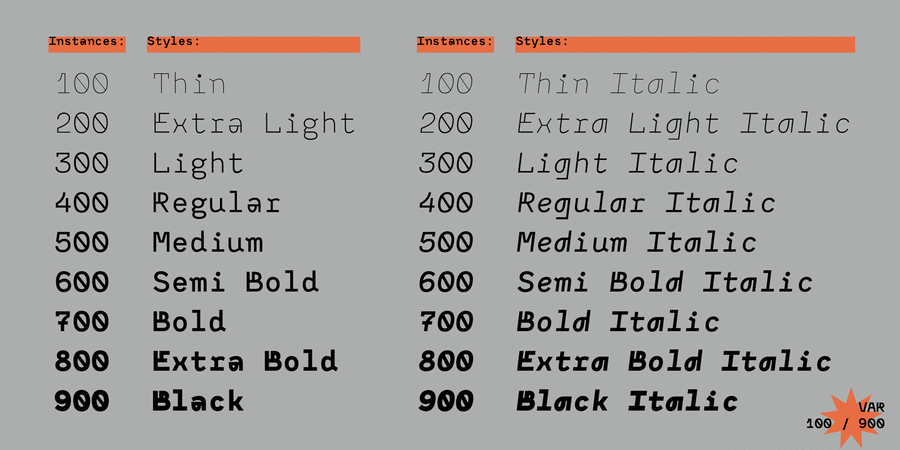
Опис гарнітури Monofontis – це сучасний моноширинний акцидентний гротеск, з неповторними символами, які допоможуть створити стильний та сучасний дизайн. Monofontis має унікальний характер, який поєднує в собі технологічність, оригінальність деталей та каліграфічну витонченість, найбільш помітну в курсивному накресленні. Monofontis відмінно працює у заголовках журналів та блогів, невеликих текстових блоках, логотипах та айдентиці, у веб-дизайні та дизайні інтерфейсів, плакатах та рекламі. Родина Monofontis чудово підходить для дизайну таблиць, колонок, чітких і жорстких макетів та програмного коду. Гарнітура включає 9 насиченостей від тонкого до жирного, та пропонує широку мовну підтримку. Monofontis складається з 18 накреслень: 9 прямих та 9 курсивних. Авторка гарнітури: Марія Вайнштейн Арт-директор: Кирило Ткачов у 2020 році.
Особливості сімейства шрифтів MonofontisХіт десятиліття:
Асоціації з сімейством шрифтів MonofontisОсобистість і характер гарнітури:
міський, прозорий, тонкий, холодний, скляний, гострий, крихкий, дротяний, ламаний, футуристичний, техногенний, твердий, чіткий, легкий, сучасний, машинний, інженерний, урбаністичний, худий, незграбний, дивний, самобутній, оригінальний, характерний, іронічний, грайливий, молодіжний, цікавий, гнучкий, індустріальний, сталевий, штучний, технічний, якісний, залізний, різкий, комп'ютерний, сильний, архітектурний, грубий, брутальний, впевнений, військовий, важкий, суворий, надійний, міцний, електронний, тусовочний, клубний, двіжняковий, прямокутний, стабільний, стійкий, мотивуючий
техніка, прилад, архітектура, наука, Місто, технології, фантастика, гаджет, девайс, айтішник, айті, IT, конструктор, креслення, інженер, автоматика, урбаністика, електроніка, дизайн, рентген, верстат, інструмент, завод, промисловість, електростанція, енергетика, машинобудування, страйкбол, хакер, гра, код, комп'ютер, програмування, залізо, робот, комп'ютерна гра, архітектор, авто, селфі, кубики, розваги, нічний клуб, вечірка, тусовка, кіберспорт, паливо, кіно Гарнітура асоціюється з віком: